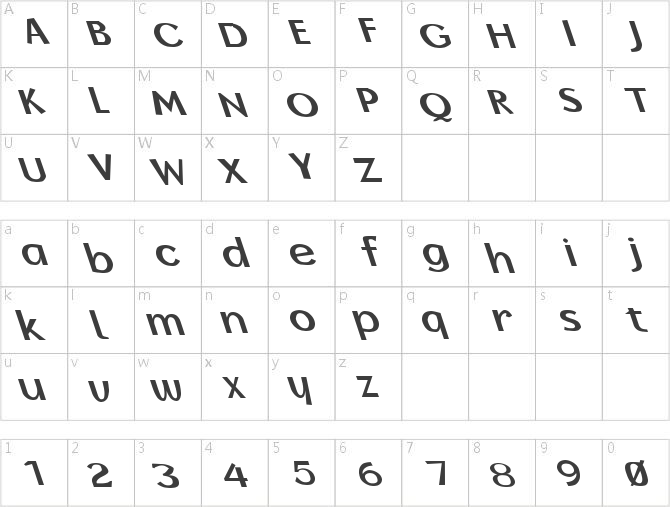
Borzoi Bold Lefty 詳情頁(yè)
Borzoi Bold Lefty字體字庫(kù)是一款讓人賞心悅目、百看不厭的英文字體,適合各類廣告和產(chǎn)品包裝設(shè)計(jì)應(yīng)用,字體大小0.06MB,格式為ttf字體,上傳用戶是誠(chéng)澤永信,作者/版權(quán)方為未知